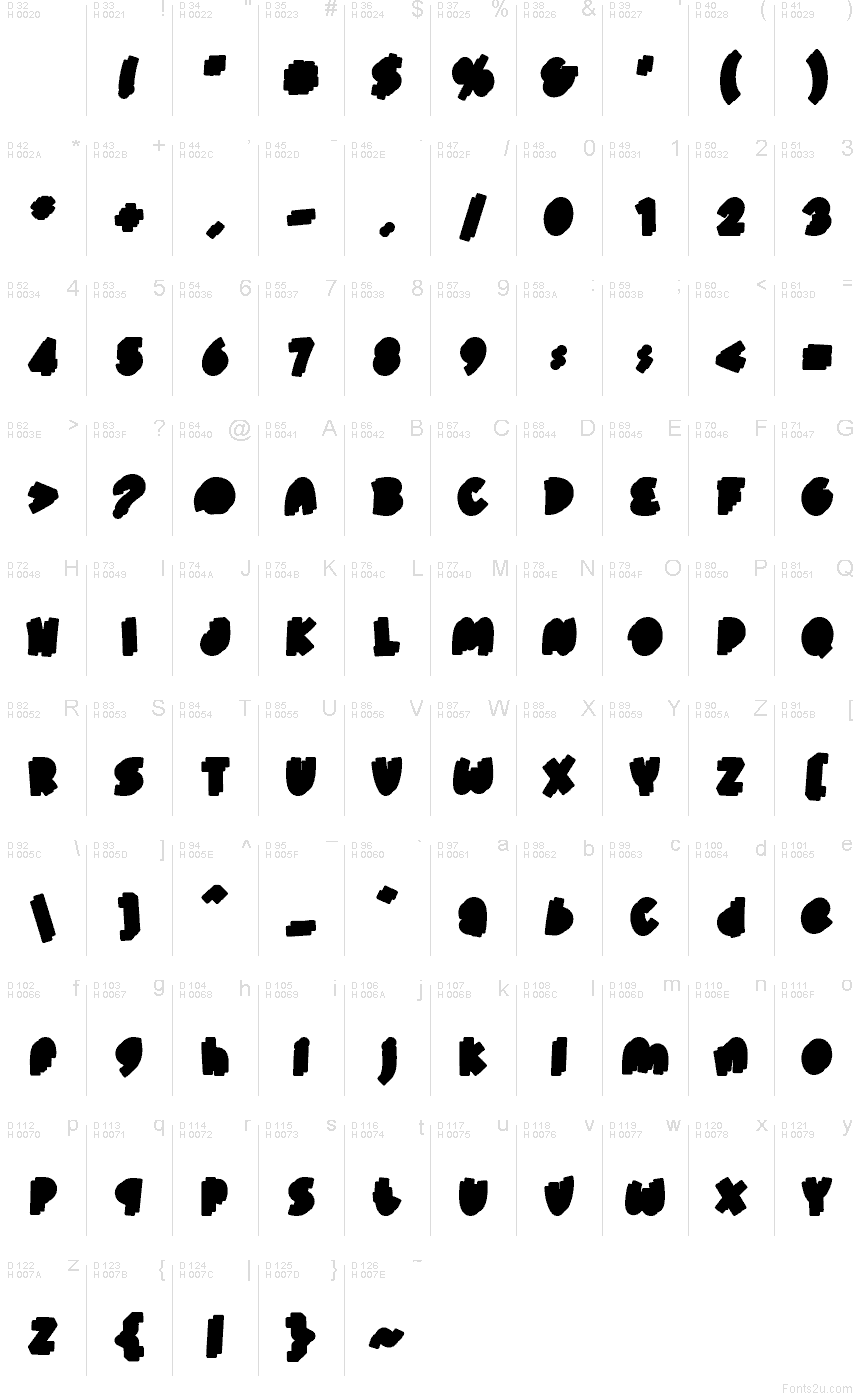
Rhuma Sinera Shadow di Mabhal Studio è un font display cartoon gratuito con una silhouette gonfia, quasi come carta ritagliata, e un ritmo allegramente irregolare. Le sue lettere spesse e arrotondate si affollano, mentre le altezze variabili e i bordi morbidi e bombati rendono la forma della parola simile a una costruzione manuale piuttosto che a una composizione tipografica.
Usa questo font gratuito per copertine di libri per bambini, packaging di giocattoli, branding di snack, poster per feste e titoli animati. Funziona meglio in brevi frasi, dove le forme dense si leggono come un unico elemento grafico audace senza perdere la loro giocosa instabilità.